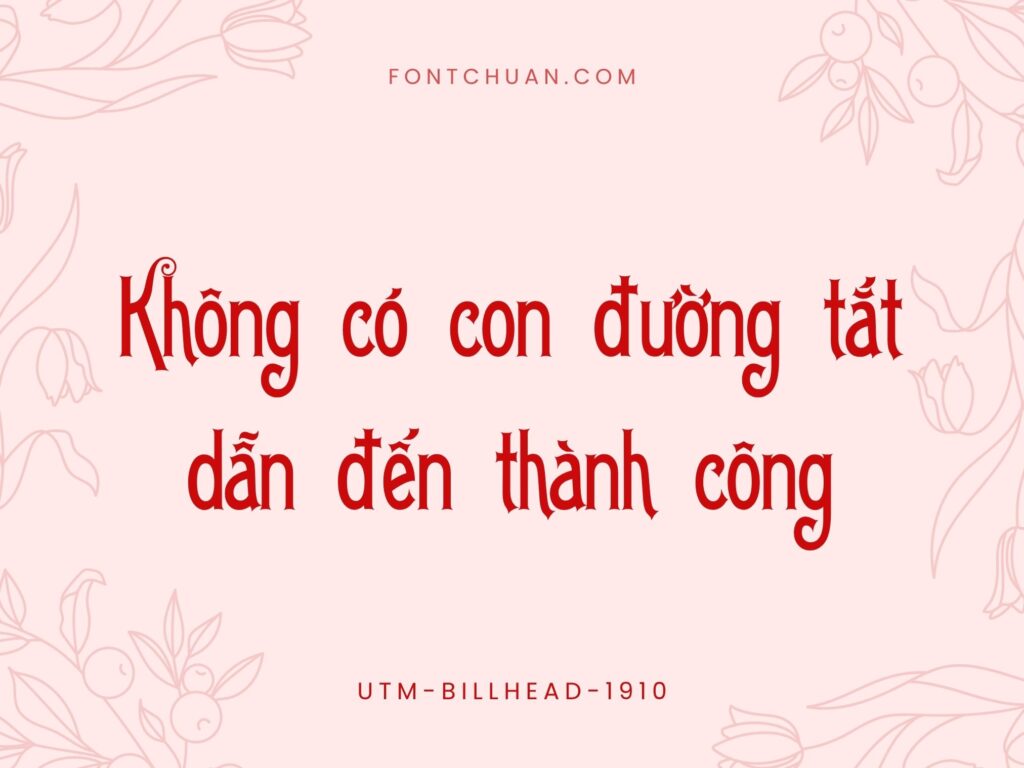
Font UTM Billhead 1910 Việt Hóa
UTM Billhead 1910 là phiên bản Việt hóa của font chữ LHF Billhead 1910, một kiểu chữ decorative/display mang phong cách Font Vintage, được thiết kế với các đường nét trang trí tinh xảo và phức tạp, gợi nhớ đến các biển hiệu và tiêu đề từ đầu thế kỷ 20. Font này nổi bật với các ký tự in hoa có sự hiện diện mạnh mẽ, chân chữ sắc nét và các đường cong độc đáo, tạo nên vẻ đẹp cổ điển, sang trọng và tinh tế. Phiên bản Việt hóa đã được thực hiện, hỗ trợ đầy đủ tiếng Việt cùng hơn 100 ngôn ngữ khác. Đây là một trong những font được cộng đồng thiết kế sưu tầm và chọn lọc nhằm đáp ứng nhu cầu đa dạng trong thiết kế.
UTM Billhead 1910 có cấu trúc chữ với các nét trang trí phức tạp và độ tương phản cao, tạo nên sự nổi bật và thu hút. Font này phù hợp cho các ứng dụng như thiết kế tiêu đề, logo, biển hiệu, áp phích và các ấn phẩm in ấn yêu cầu sự cổ điển và nghệ thuật. Bên cạnh đó, nhờ sự tinh tế trong các đường nét và chi tiết trang trí, UTM Billhead 1910 cũng có thể được sử dụng như một Font chữ spa, mang đến cảm giác sang trọng, nhẹ nhàng và thư giãn cho các thương hiệu chăm sóc sức khỏe, spa và làm đẹp. Các ngành nghề như quảng cáo, giáo dục, công nghệ và bất động sản đều có thể tận dụng font này để tạo điểm nhấn độc đáo trong thiết kế.